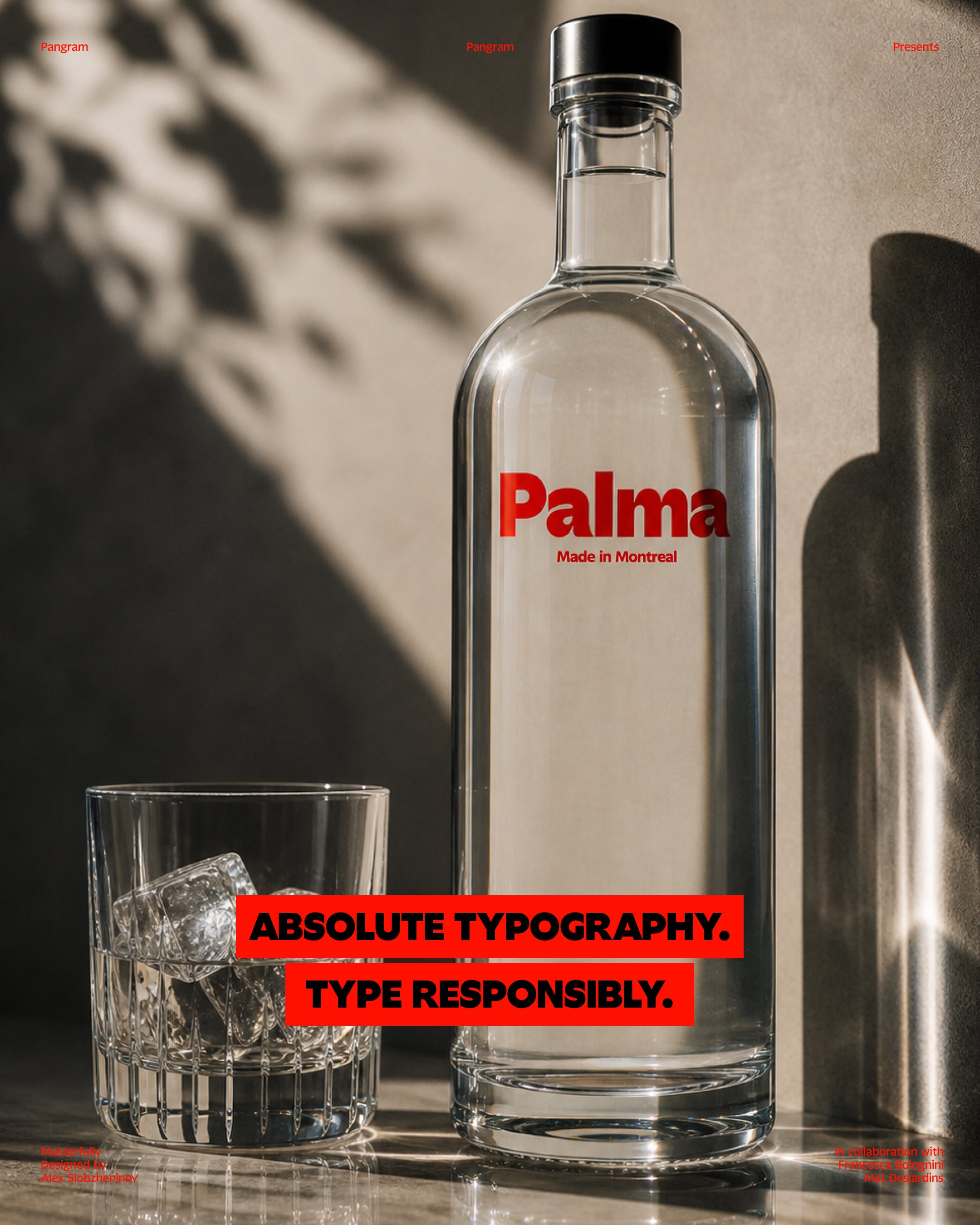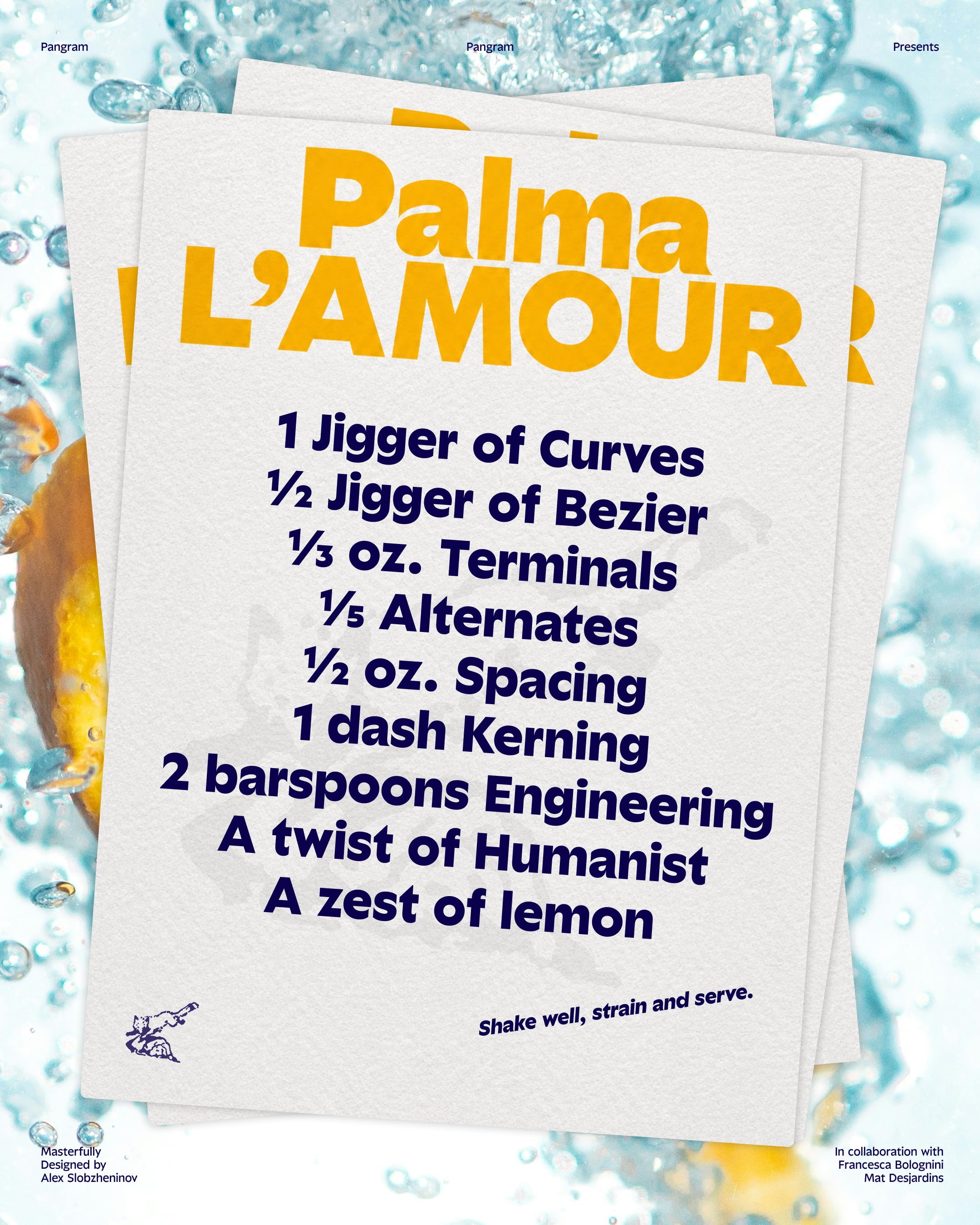
Palma Fizzy
A spritzy sans family of a dual geo-humanist nature.
Designed for versatility, the typeface spans across the two genres, combining the best of both worlds.
One part of the family is toned-down and humanist, featuring open shapes, natural letterforms and balanced proportions, intended for subtle roles when reading comfort and legibility are crucial. The other subfamily, Fizzy, cranks up the flavor all the way up, turning the shapes geometric, tightening spacing and making details more crisp and accentuated, perfect for juicy large-size uses.
Palma is loosely inspired by the giants like Antique Olive, Johnston and Avenir, but treats the references lightheartedly, going for a different route with a flair. This duality becomes especially clear in the structure of the family itself. Palma is divided into two complementary subfamilies that explore the concept from different angles. The first leans toward the humanist side of the spectrum. Here, shapes are open and relaxed, proportions are balanced, and the overall rhythm favors readability and comfort. The letterforms carry a natural flow that makes them particularly well suited for extended reading, editorial design, and any situation where subtlety and clarity take priority. The second subfamily, called Fizzy, turns up the energy considerably. While sharing the same underlying DNA, the Fizzy styles push the geometry further: shapes become more circular and defined, spacing tightens, and details appear sharper and more assertive. The result is a brighter, more graphic voice that shines in display settings, headlines, posters, and branding applications where a stronger typographic presence is needed. Where the humanist styles are calm and composed, Fizzy feels vibrant, crisp, and full of personality. Together, these two directions allow Palma to operate across a surprisingly wide stylistic range. Designers can move seamlessly between a softer, more neutral tone and a more expressive and graphic one, all while maintaining a cohesive typographic system. This versatility makes the family particularly adaptable for projects that require both quiet text settings and impactful display moments within the same visual language. Although Palma isn’t conceived as a traditional “workhorse” grotesk, it was carefully designed to perform across many practical scenarios. Its structure supports comfortable reading in longer texts while still offering enough character to stand out in headlines and larger compositions. The interplay between its humanist and geometric tendencies allows it to shift effortlessly from understated editorial typography to bold visual statements. The family includes 28 styles in total, organized into two subfamilies of seven weights, each accompanied by matching italics. In addition to the static fonts, Palma is also available as a variable font, providing continuous control across the weight range and allowing for even greater flexibility in responsive and performance-driven typographic environments. Palma also includes a wide set of OpenType features to support professional typesetting workflows, along with broad language support covering a large range of Latin-based writing systems. With its balanced mix of personality, adaptability, and typographic precision, PP Palma aims to offer designers a tool that can move comfortably between quiet functionality and expressive flair—sometimes serious, sometimes playful, but always unmistakably lively.
Palma Fizzy est variable
Fonctionnalités de Palma Fizzy
Single-storey a
Single-storey g
Legible l
Geometric &
Case-Sensitive Forms
Tabular Figures
Un humaniste familier avec Fizz.
PP Paloma est une famille de caractères sans empattement dynamique, à la fois géo-humaniste et pétillante. Conçue pour la polyvalence, cette police embrasse les deux genres, combinant le meilleur des deux mondes. Paloma s'inspire librement de grands noms comme Antique Olive, Johnston et Avenir, mais traite ces références avec légèreté, empruntant une voie différente et pleine d'élégance.
Une partie de la famille, plus sobre et humaniste, se caractérise par des formes ouvertes, des caractères naturels et des proportions équilibrées, idéale pour les applications discrètes où le confort de lecture et la lisibilité sont primordiaux. L'autre sous-famille, Fizzy, est résolument dynamique : les formes sont géométriques, l'espacement est réduit et les détails sont plus nets et précis, parfaits pour les grandes tailles.
Bien qu'elle ne soit pas une police grotesque « de travail » classique, Paloma est conçue pour s'adapter à une vaste gamme d'applications, des textes longs aux titres et affiches ; d'une neutralité discrète à une force expressive marquante. La famille de polices se décline en 28 styles : 2 sous-familles de 7 graisses, plus les italiques ; toutes sont également disponibles au format variable. Elle intègre de nombreuses fonctionnalités OpenType pour la composition professionnelle et prend en charge un grand nombre de langues latines.